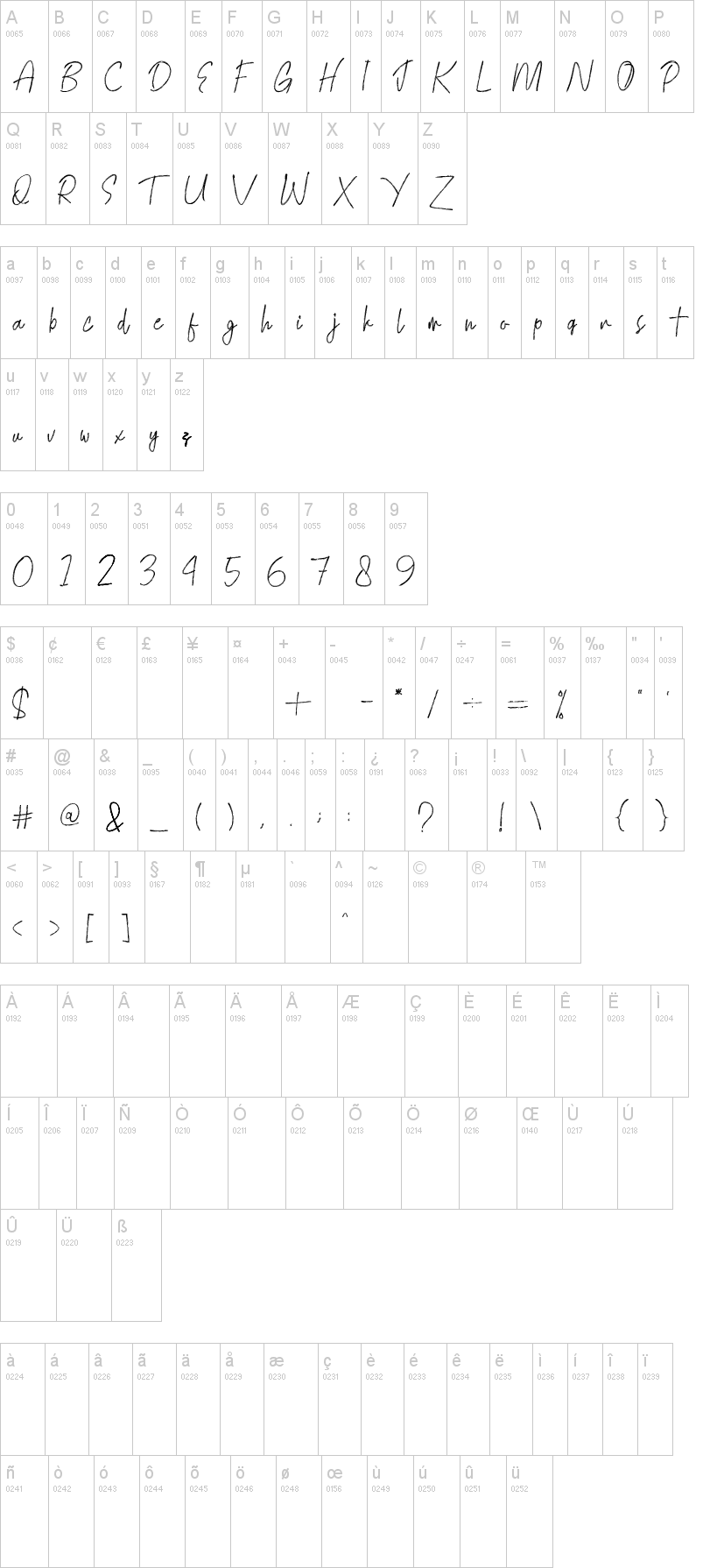
? Mighty 字体是一款由美国设计师 Michael Parson 创作的新款古典英文字体。它拥有清新的英文字体风格,细节丰富,字形清晰,笔画流畅,有助于增强文档的可读性。Mighty 字体可用于多种文档和印刷品,包括书籍、报纸、杂志、广告等,可以提供更好的可读性和视觉效果。内容介绍
Mighty是一款非常不错的手写艺术字体,具有很好的视觉感,适合于文化类的宣传设计、商业类品牌的广告和产品包装设计以及个性化文字排版等较多场景。